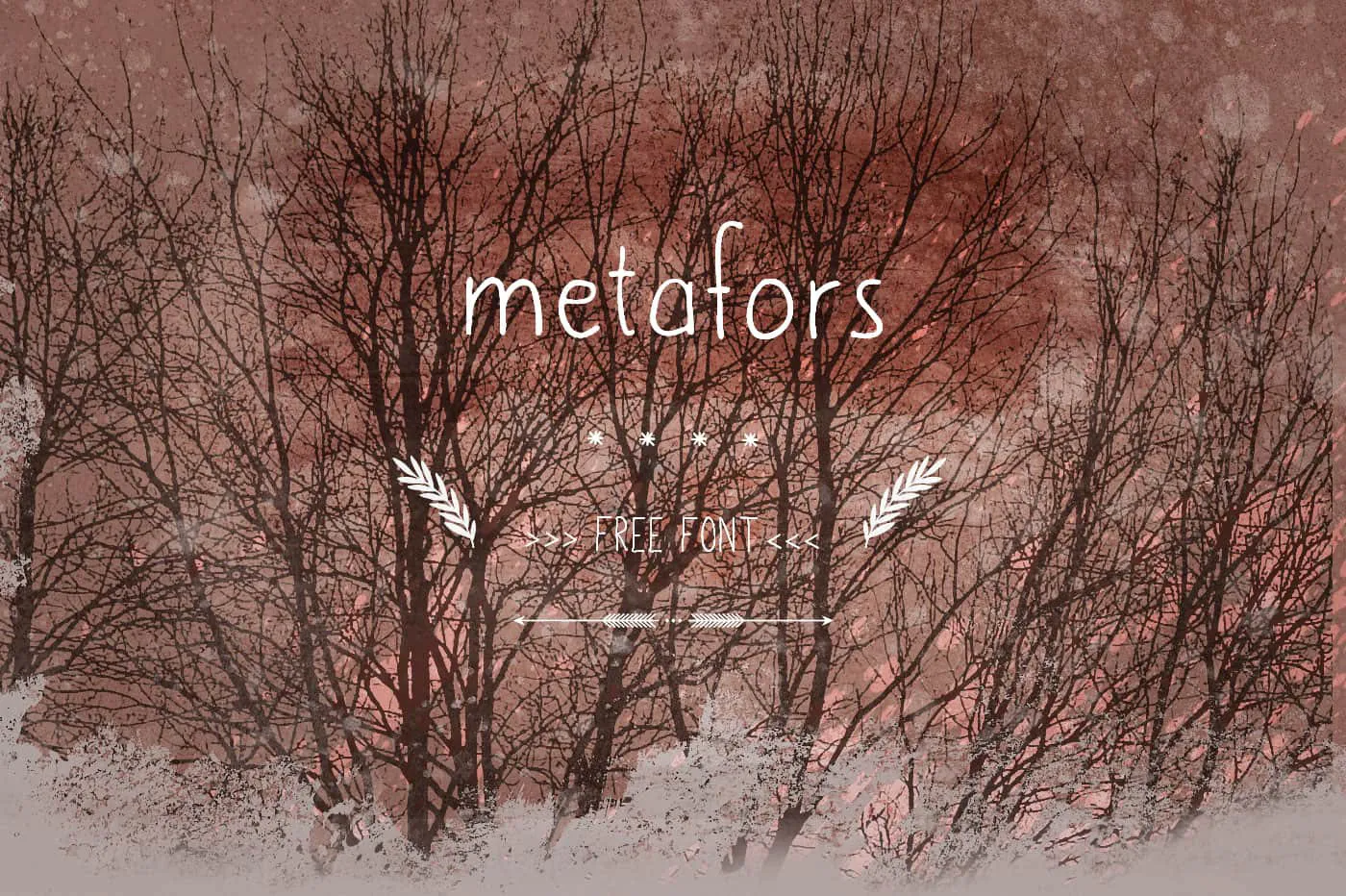
A “Metafors Font” é uma fonte inspirada na escrita à mão livre que oferece um toque autêntico e um brilho suave. Esta elegante escolha de fontes foi criada pelo designer Hamilton, trazendo uma personalidade única a qualquer projeto. O download inclui tanto o formato TTF quanto OTF, permitindo grande flexibilidade ao uso da fonte em diferentes sistemas. Este é um recurso que encoraja você a explorar suas habilidades com esta fonte e experimentar novos estilos de escrita à mão livre. Se encontrarem algo incrível usando essa fonte, Hamilton adoraria saber sobre isso – apenas deixem uma ligação nos comentários abaixo para eles se inscreverem. Muito obrigado por usar a Metafors Font!